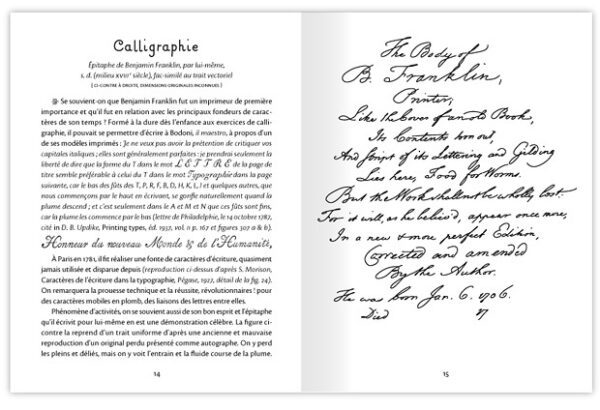
CADEAUX
Script types for the blind — a revival: Aui.ttf
CRÉATION À BUT NON LUCRATIF D’UNE POLICE IMITÉE DES PREMIERS CARACTÈRES D’IMPRIMERIE POUR... AVEUGLES.
«Des créateurs de caractères manuscrits, créant des œuvres insolites, rêvant parfois d’établir de nouveaux canons pour remplacer ceux du romain dominant, ont quitté le lit du fleuve de la lettre (qui, comme on le sait débouche sur la mer d’Arial) pour remonter de tortueux affluents, en périples la plupart du temps sans débouché mais jamais sans intérêt, sinueux détours pareils aux boucles, volutes et entrelacs dont ils décoraient leurs alphabets. Or ces motifs avaient un nom, on les appelait des... CADEAUX. (...) «C'est sur ce terrain gracieux qu'a lieu cette renaissance, entreprise comme une distraction et présentée dans ces pages dans son imparfaite version 1.0, sans aucun but industriel.»
A NONPROFIT DIGITAL RECREATION OF THE FIRST PRINTING TYPES FOR... THE BLIND.
“Designers of script types, creating unusual features, willing to establish new canons to replace the prevalent Roman, left the letters’ riverbed (which, as we all know, leads to the Arial Sea ) to run up tortuous tributaries, in interesting though openingless journeys, through detours similar to the flourishes and swashes they decorated their alphabets with. Which patterns bore the French name CADEAUX: gifts. (...) “Gratuitously undertaken as a distraction, this revival is shown in these pages in its imperfect 1.0 version, devoid of any commercial purpose.”